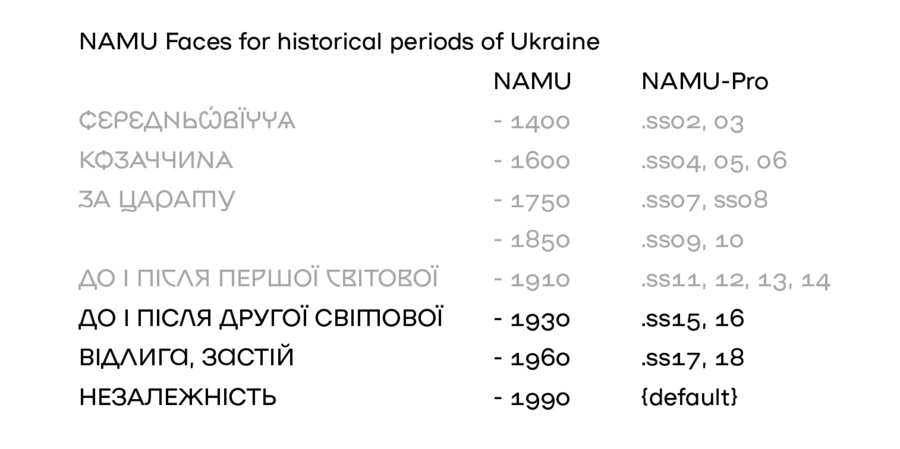
NAMU Modernism – шрифти 1930, 1960, 1990 з безкоштовної гарнітури для Національного художнього музею України. NAMU – геометричний гротеск зі смаколиками, херітажем, челенджьом та таймлайном. Переможець Red Dot 2019 у категорії «Корпоративний дизайн та айдентика». Наприкінці 2018 року Національний художній музей України та Banda презентували нову айдентику. Шрифт NAMU став основою візуального стилю. Для створення шрифту дизайнер Дмитро Растворцев з головою занурився у дослідження музейного фонду, архівних документів і накреслень стародавніх літер. У результаті фінальний шрифт NAMU має 20 стилістичних наборів у версії NAMU Pro та 9 окремих накреслень для кожного історичного періоду. Усі шрифти NAMU є безкоштовними для комерційного та некомерційного використання. Але файли шрифтів не можна декомпілювати. Ліцензія Creative Commons CC BY-ND 4.0. Шрифт розробив Дмитро Растворцев у 2018-2022 роках.
Асоціації з сімейством шрифтів NAMU ModernismОсобистість і характер гарнітури:
серйозний, переконливий, твердий, залізний, надійний, мужній, впевнений, сталевий, ностальгічний, тоталітарний, стабільний, гучний, рівний, сильний, кондовий, стійкий, політичний, комуністичний, революційний, сміливий, Простий, пролетарський, точний, прямокутний, індустріальний, техногенний, військовий, армійський, урбаністичний, грубий, робочий, мотивуючий, залізничний, амбітний, міський, незграбний, гострий, жорсткий, ламаний, рубаний, елементарний, різкий, чіткий, брутальний, ігровий, оригінальний, квадратний, експериментальний, дзвінкий, дивний, характерний, незвичайний, модний, цікавий, мінімалістичний, міцний, сучасний, зрозумілий, технічний, формальний, статичний, нейтральний, логічний, прагматичний, практичний, лаконічний, доступний, автоматичний, штучний, холодний, машинний, інженерний, креслярський, чистий, самостійний, архітектурний
війна, армія, зброя, машинобудування, прапор, мітинг, політика, шахта, завод, металургія, верстат, інструмент, будівництво, будматеріали, тара, склад, порт, ящик, патрони, архітектура, конструктор, креслення, техніка, промисловість, електростанція, енергетика, ремонт, урбаністика, депо, шахтар, шолом, уніформа, вагон, авіація, літак, страйкбол, взуття, коворкінг, залізниця, Місто, робочий, страйк, Протест, кубики, лего, дизайн, інтер'єр, гра, електроніка, хімія, математика, прилад, код, інженер, автоматика, наука, меблі, мода, технології, інновації, девайс, гаджет, банкнота, монета, вода, небо Гарнітура має ознаки стилів: